此字柔中带刚,富有力量感,如外表儒雅,心有傲骨的热血书生,寒窗苦读,酝酿许久,不鸣则已一鸣惊人,以笔为剑,披荆斩棘,欲将那状元之位收入囊中。
该款字体给人以十足的美感,强烈的视觉呈现效果;整套字库采用方正优雅的做法是此套字库的亮点。看上去稳重端庄,大气开阔。
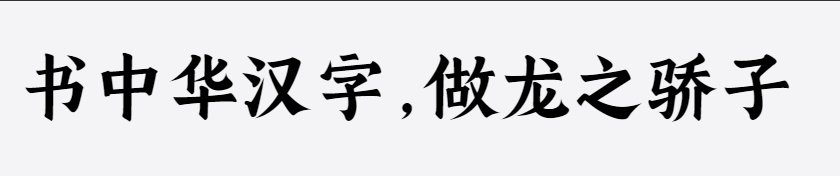
字体笔画整体偏粗且粗细一致,属于无衬线体字体。字体上圆下方,体型方正,整体稳重又不失可爱。字体上导大圆,下导小圆。